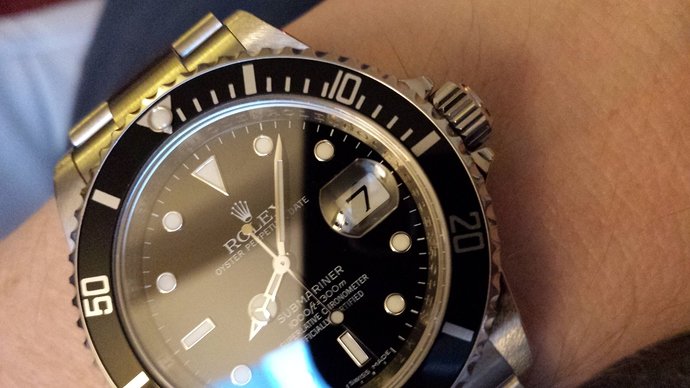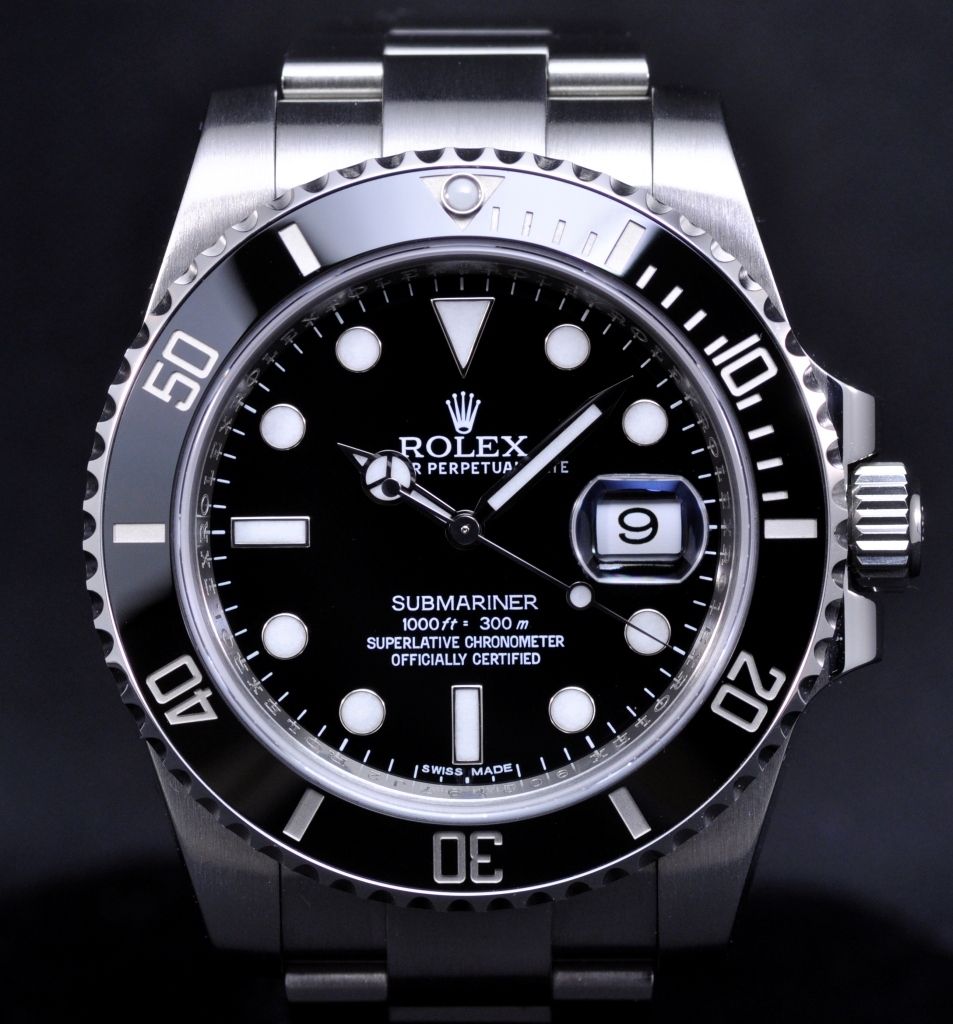
Keek vanmorgen naar de datum van mijn vrij recente sub date…
Dacht eerst dat ik genept was…wat een vreemde fonts keuze van Rolex.
De 7 lijkt wel een groter dan teken…>
Maargoed ondanks dat…Mijn Rolex is hoe dan ook top
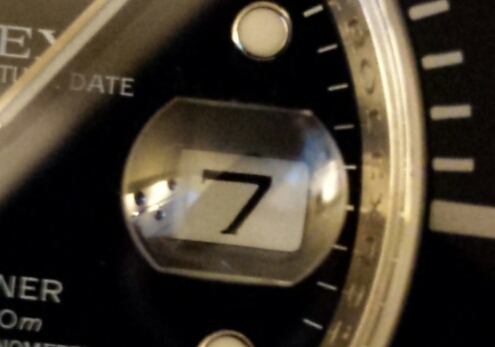
Top horloge ![]()
Niks mis mee.
Perfect toch
Mwoah…vind mijn PO 7 iets perfecter
Maar gooi hem ook niet weg hiervoor.
Na een paar jaar ziet dat er zo uit